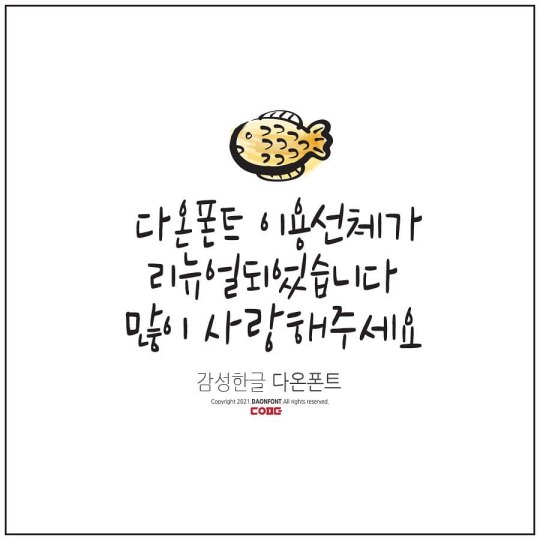
#첫줄안녕 다온폰트 이용선체가 리뉴얼 되었습니다. 멋진 일러스트와 폰트만으로 작품이 될 수 있습니다 🤘🏼 https://www.instagram.com/p/CW2OJLLFYTP/?utm_medium=tumblr
#첫줄안녕 다온폰트 이용선체가 리뉴얼 되었습니다. 멋진 일러스트와 폰트만으로 작품이 될 수 있습니다 🤘🏼 https://www.instagram.com/p/CW2N6DIlxFs/?utm_medium=tumblr